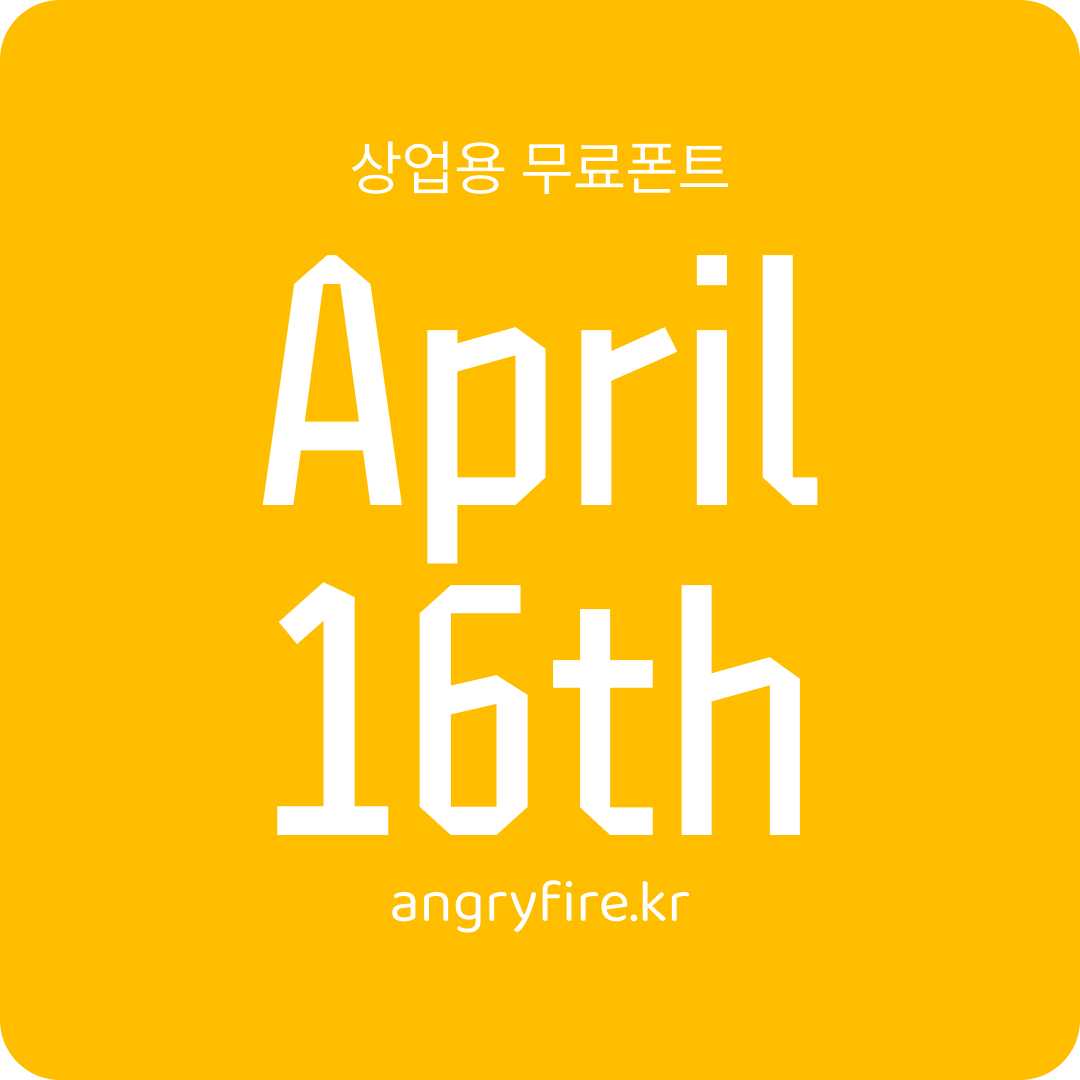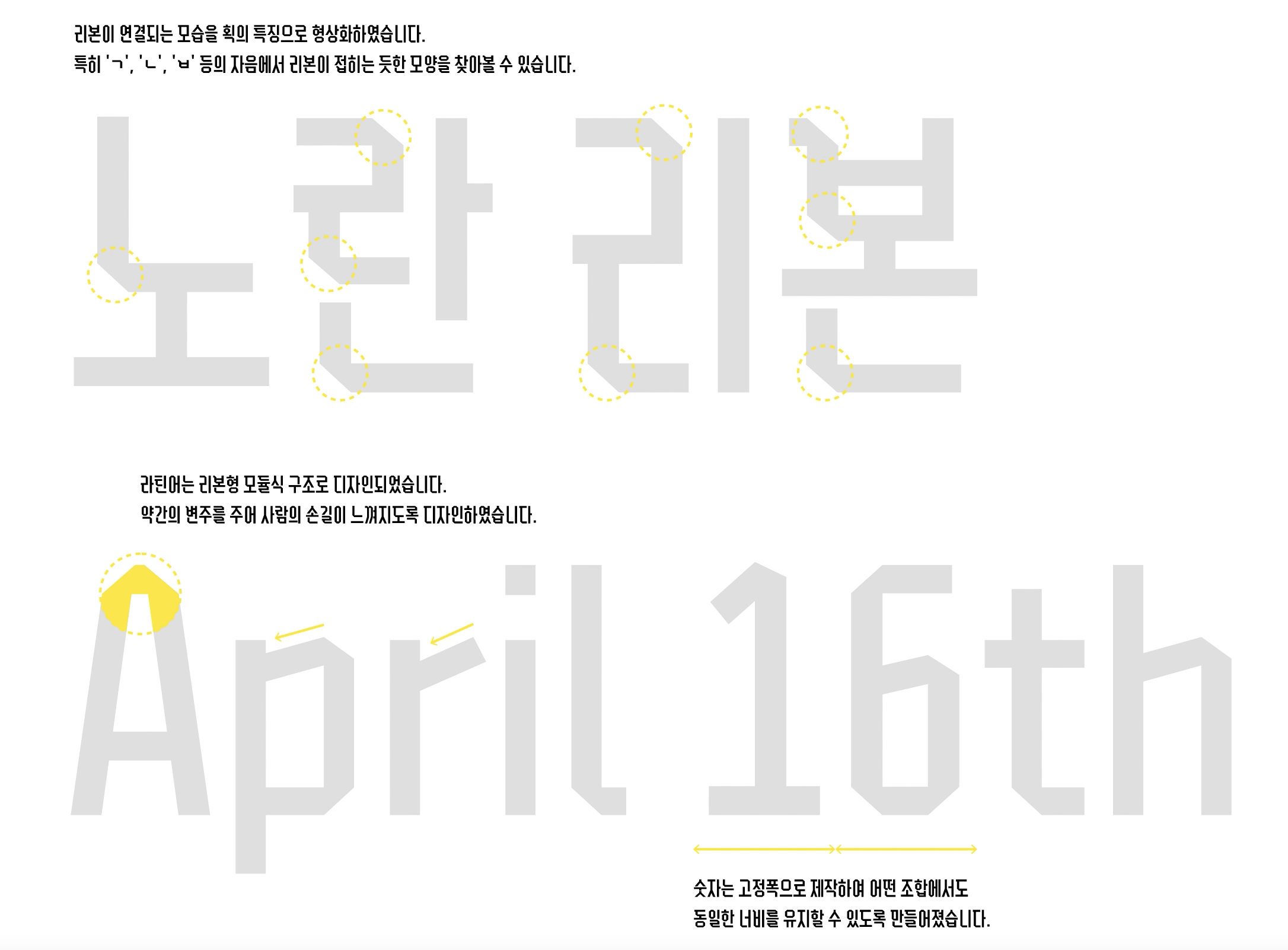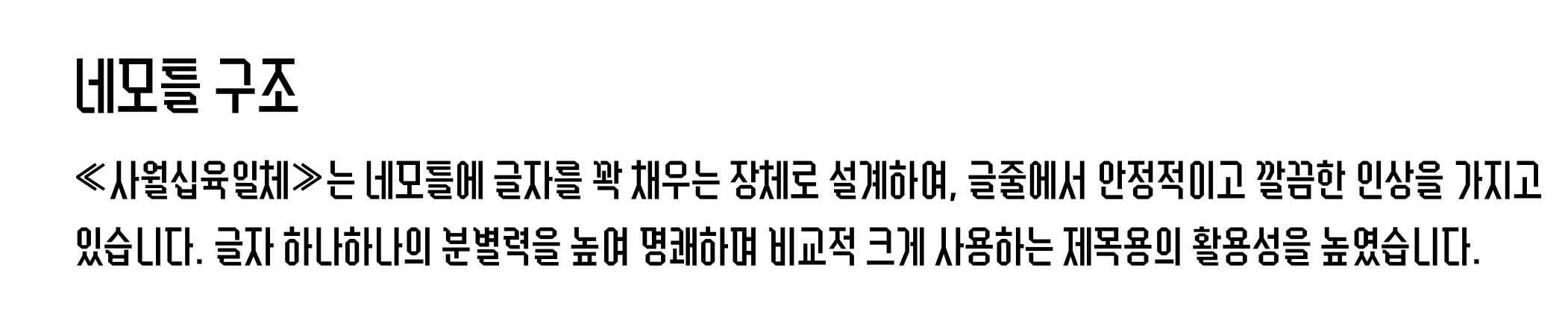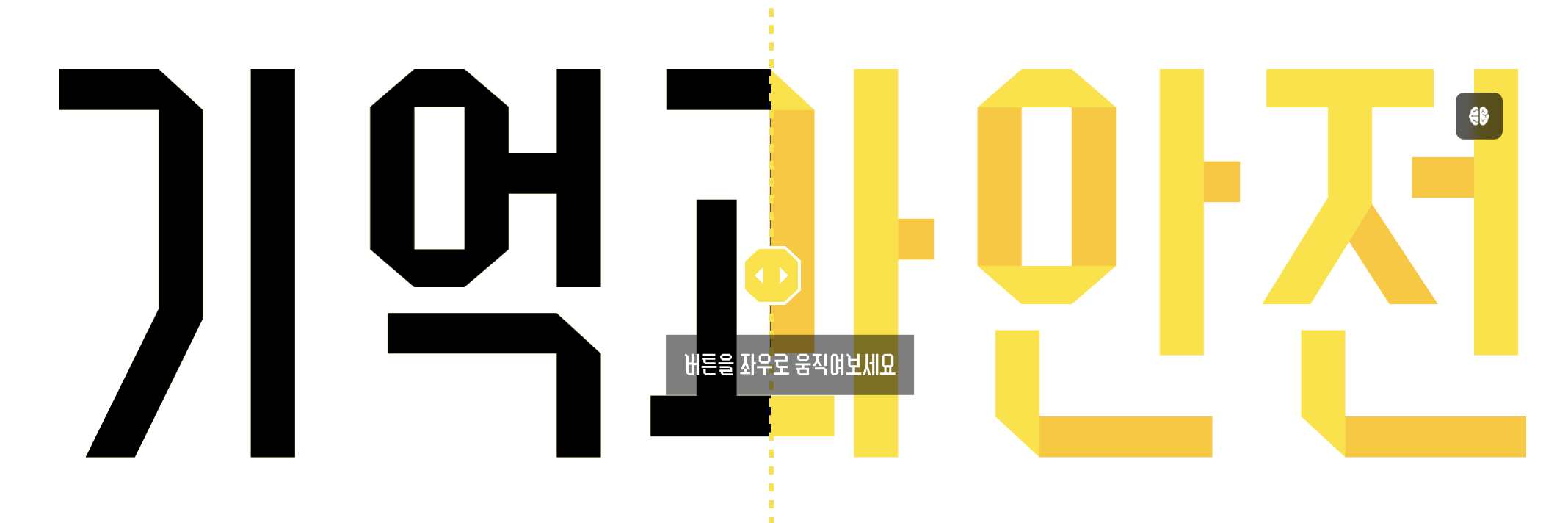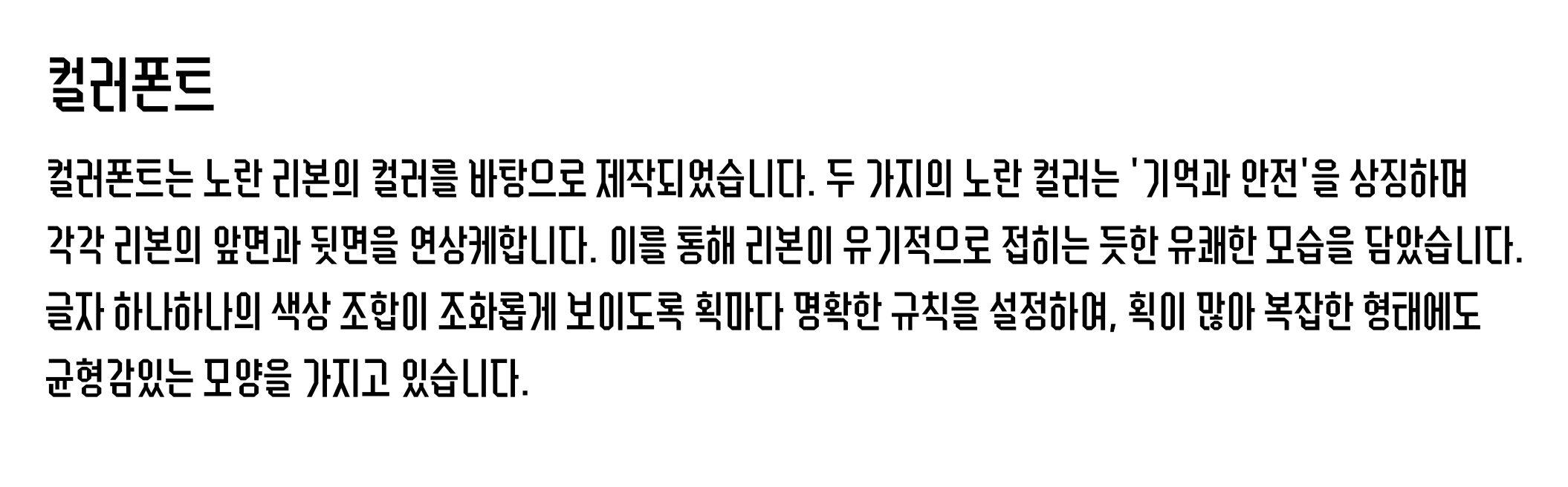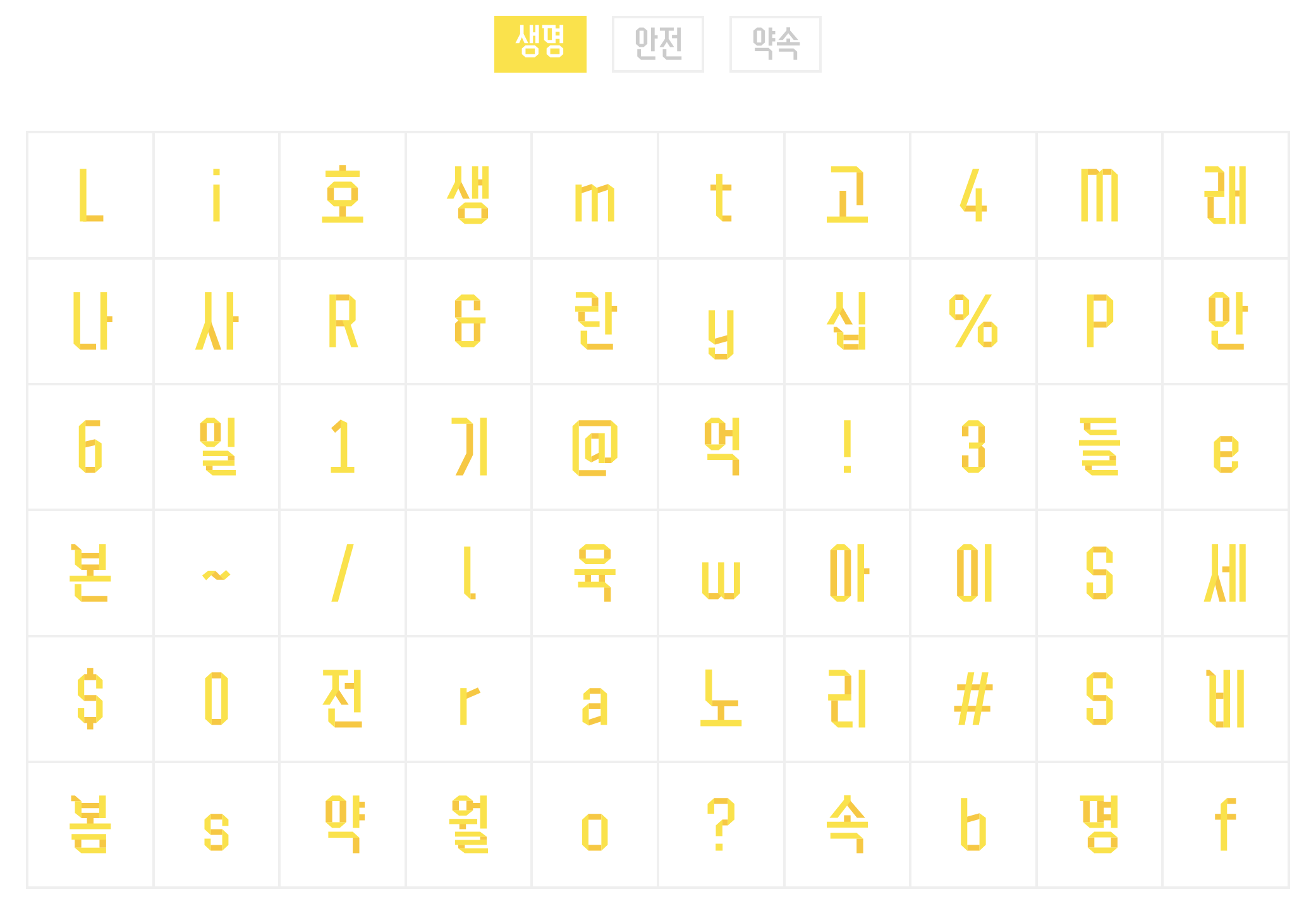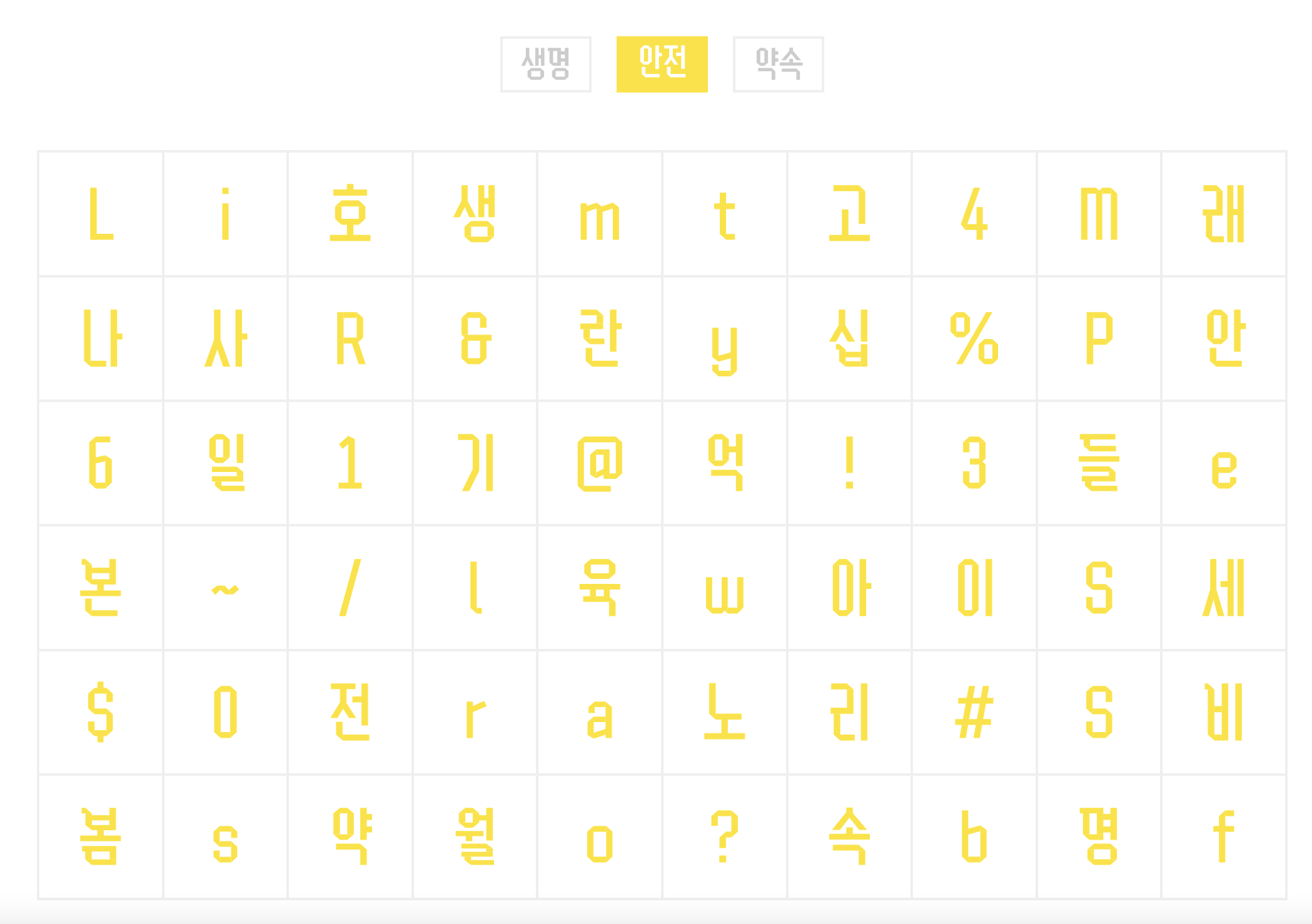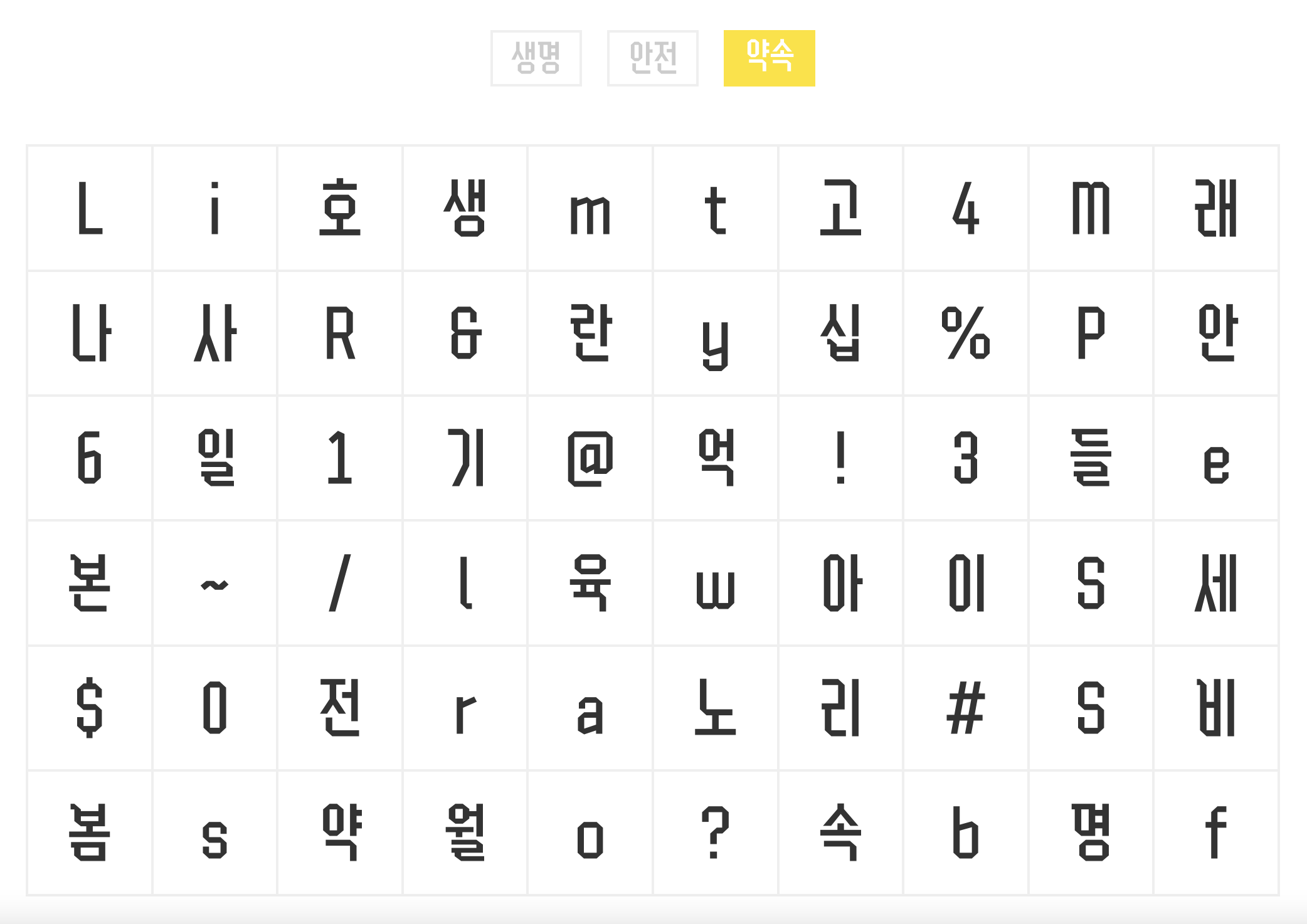
4·16재단에서 제작한 사월십육일체를 소개합니다.
사월십육일체
«사월십육일체»는 '세월호참사 10주기'를 맞아 4·16재단에서 제작한 폰트입니다. 세월호참사를 상징하는 노란 리본을 모티프로 디자인 되었으며 다양한 사용성을 고려하여 컬러폰트를 포함한 3종으로 만들어졌습니다.
서체의 특징
서체의 구성
생명: 한글 2,780자, 라틴 문자 52자, 숫자 10자, 문장 부호 205자
안전: 한글 2,780자, 라틴 문자 52자, 숫자 10자, 문장 부호 205자
약속: 한글 11,172자, 라틴 문자 52자, 숫자 10자, 문장 부호 205자